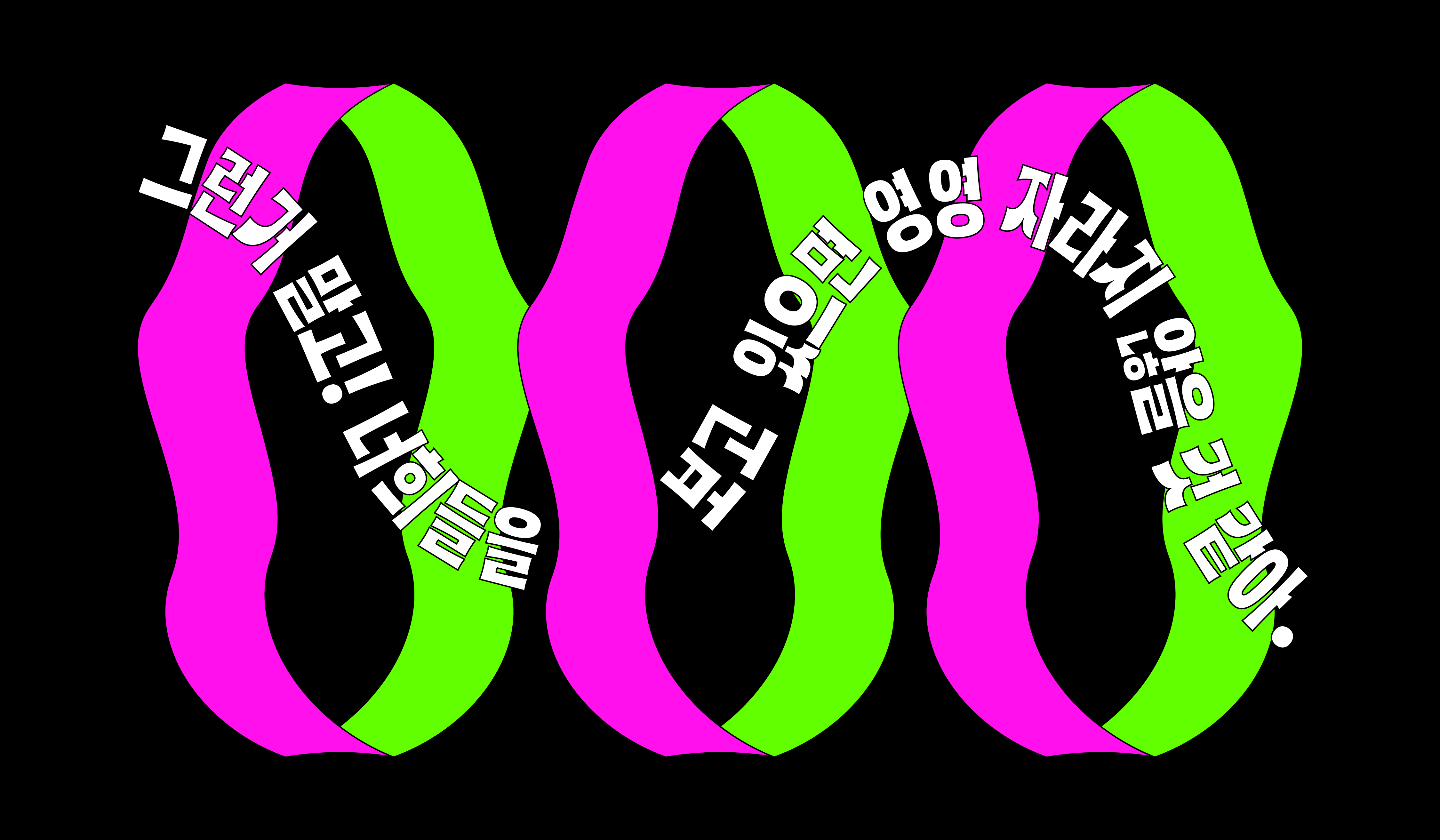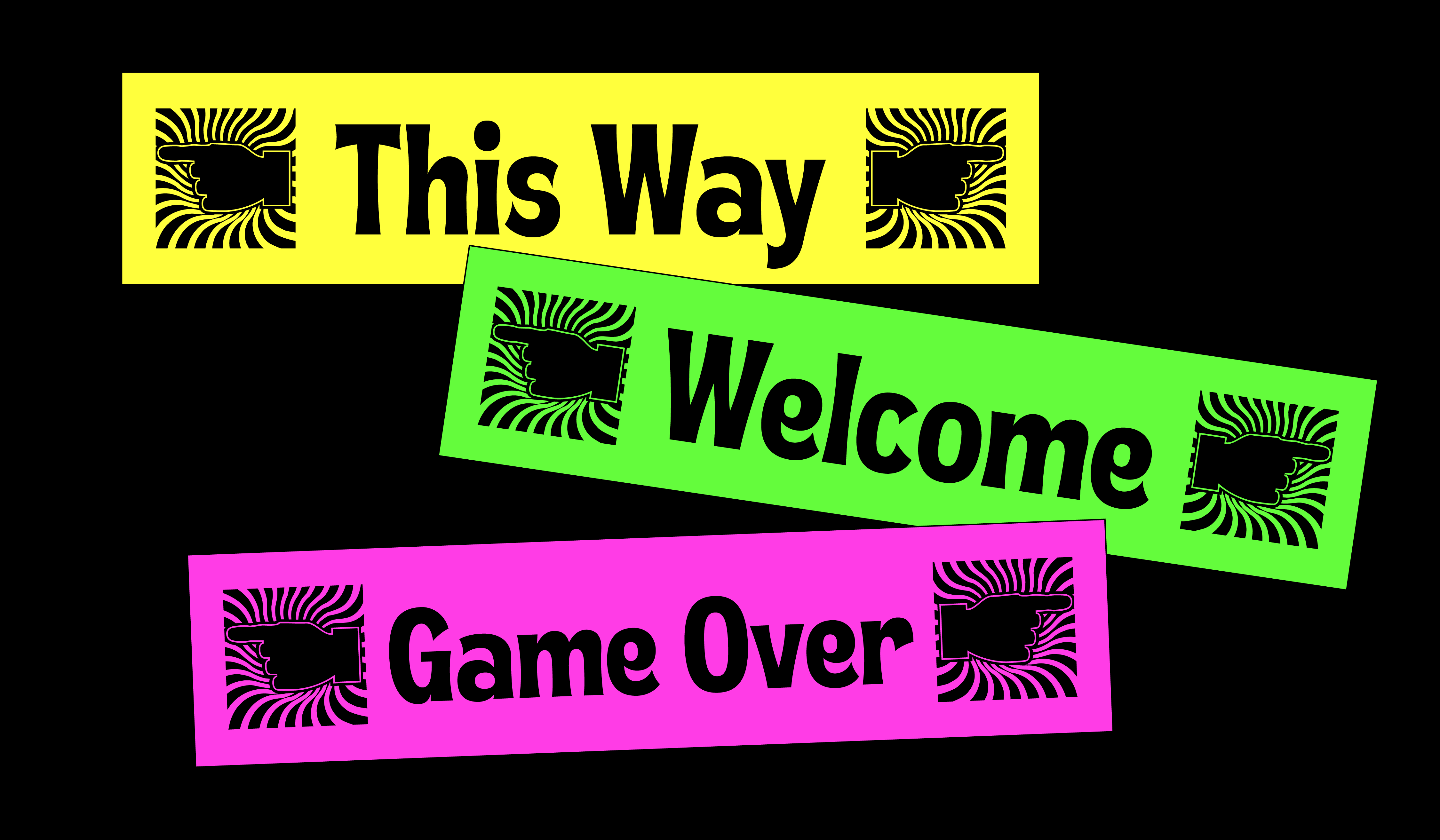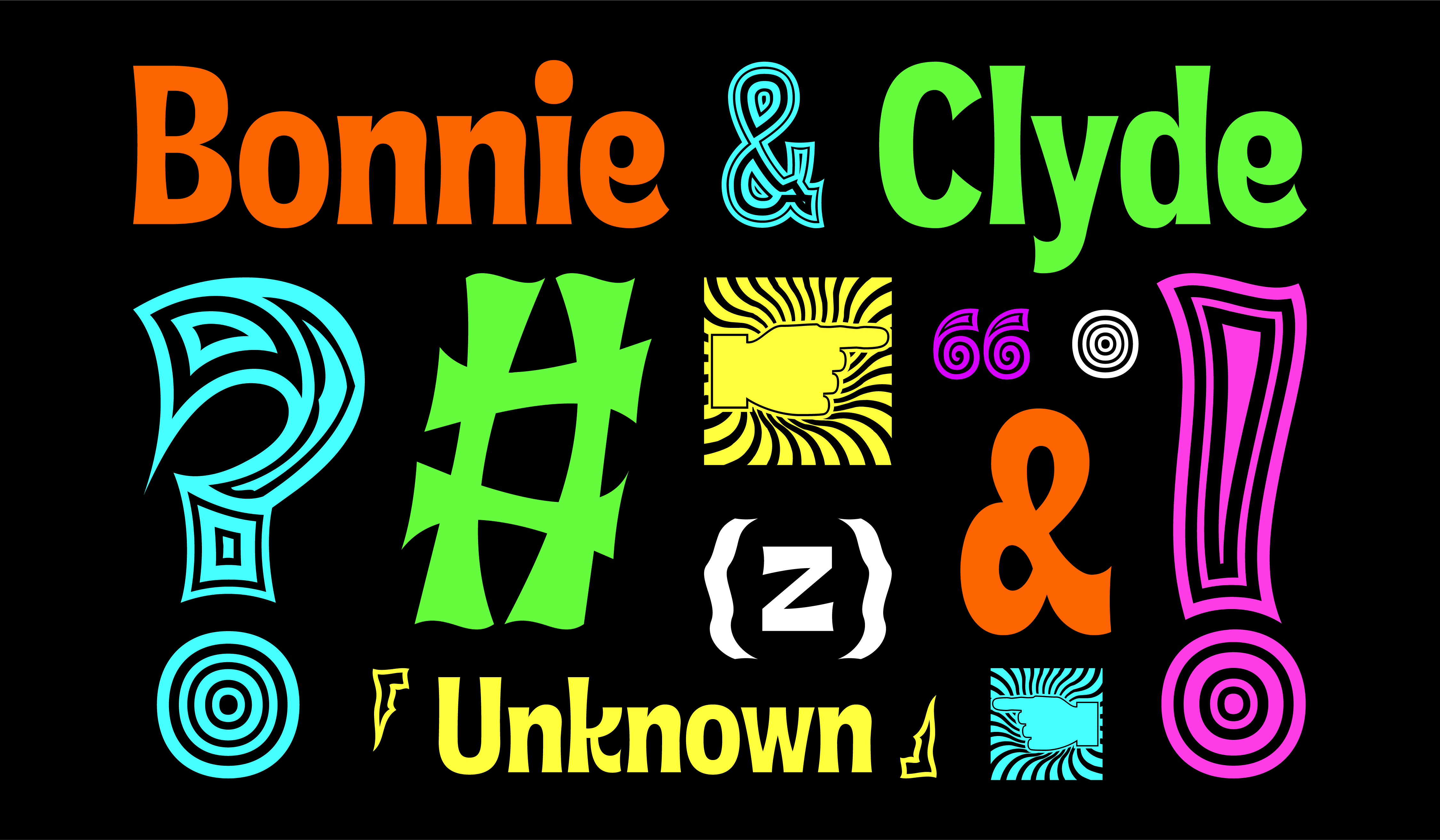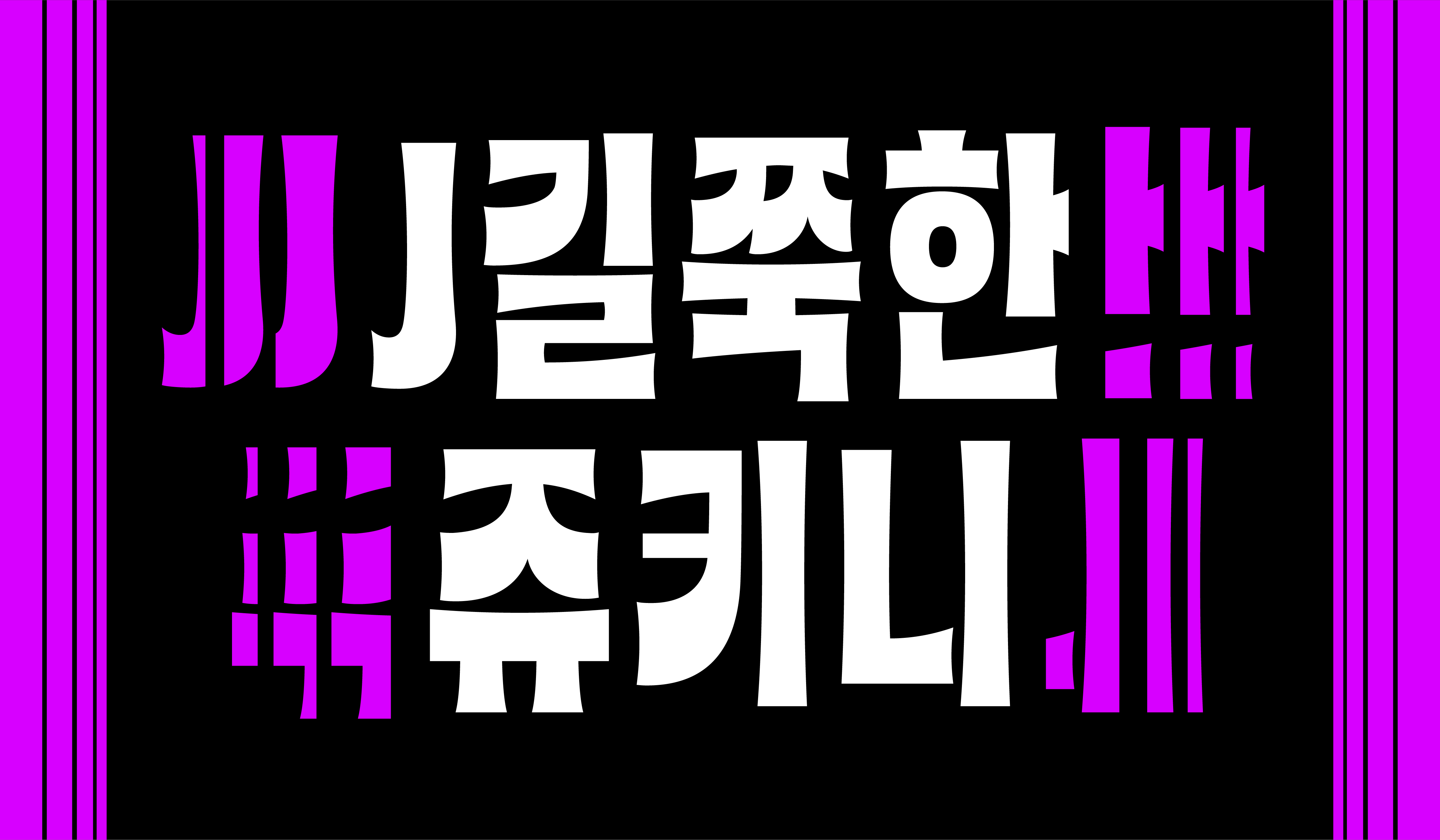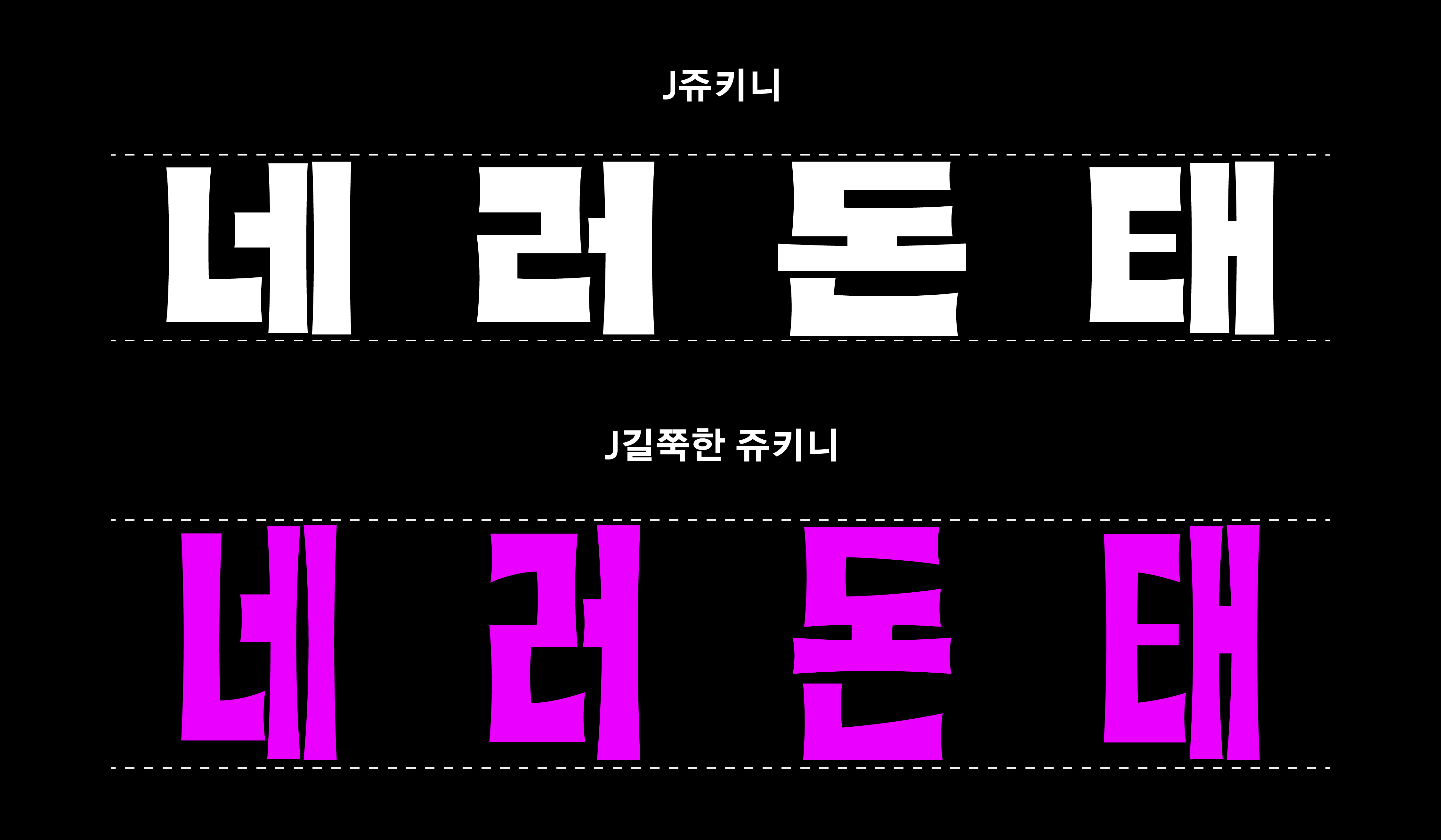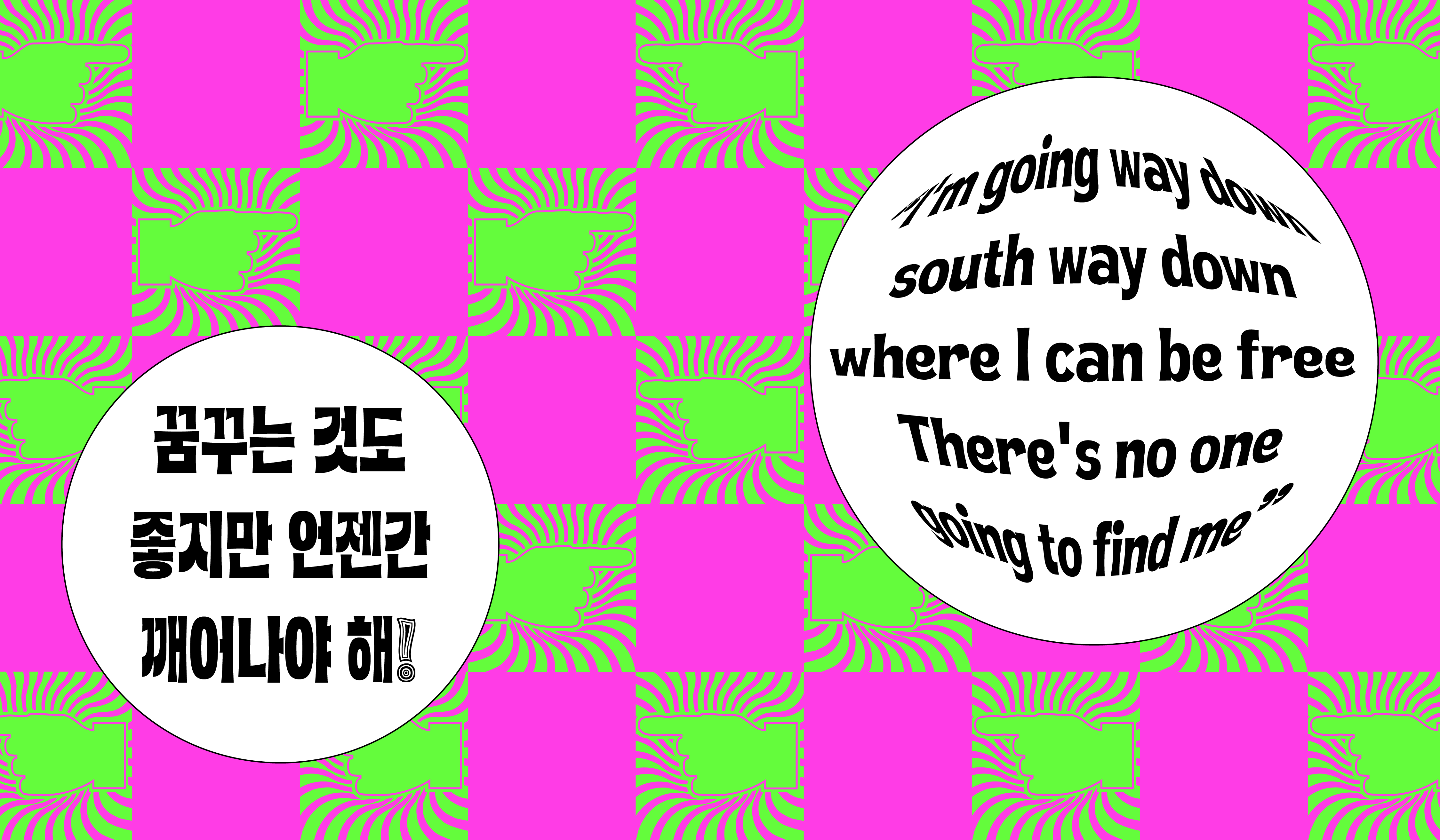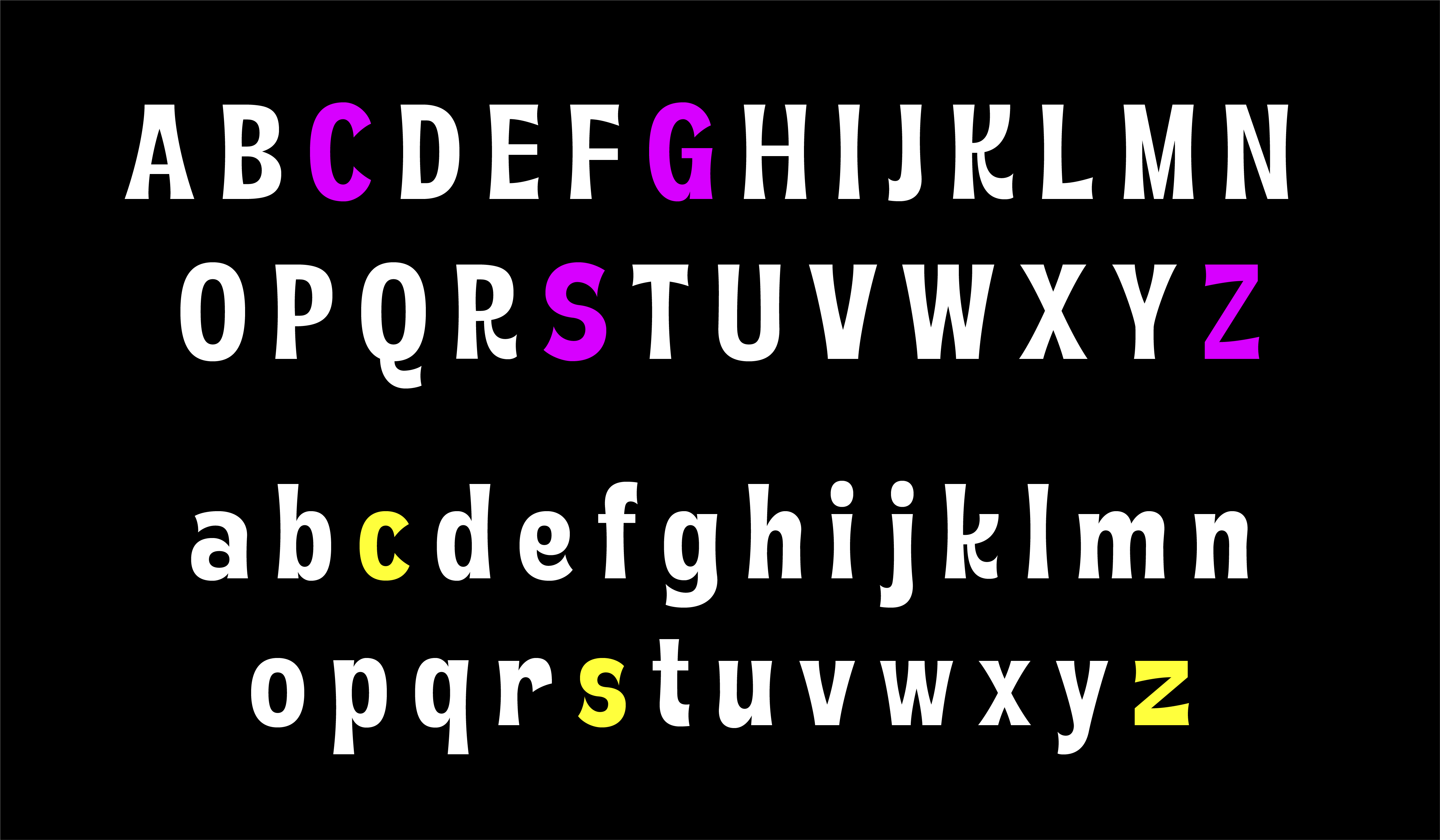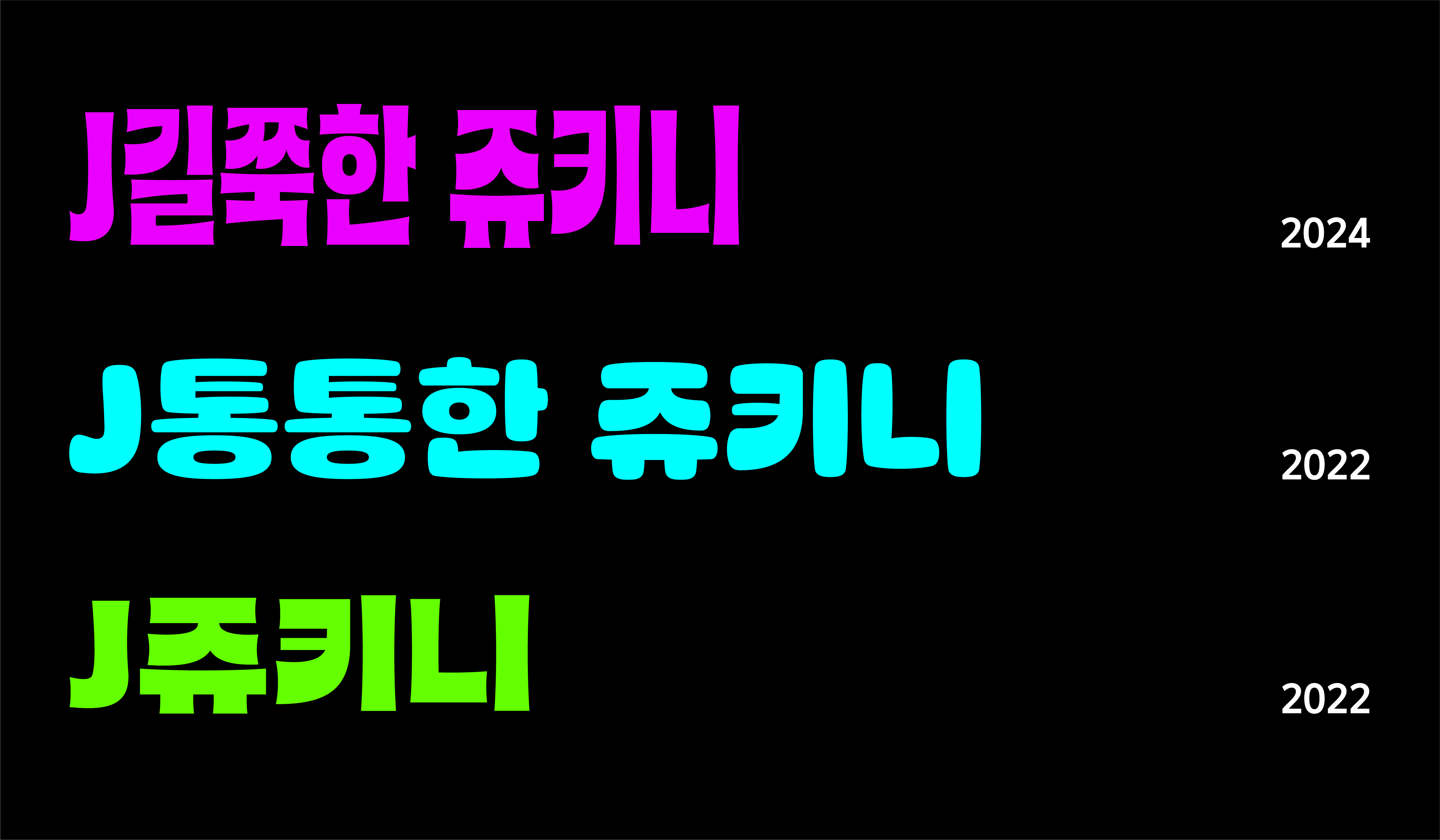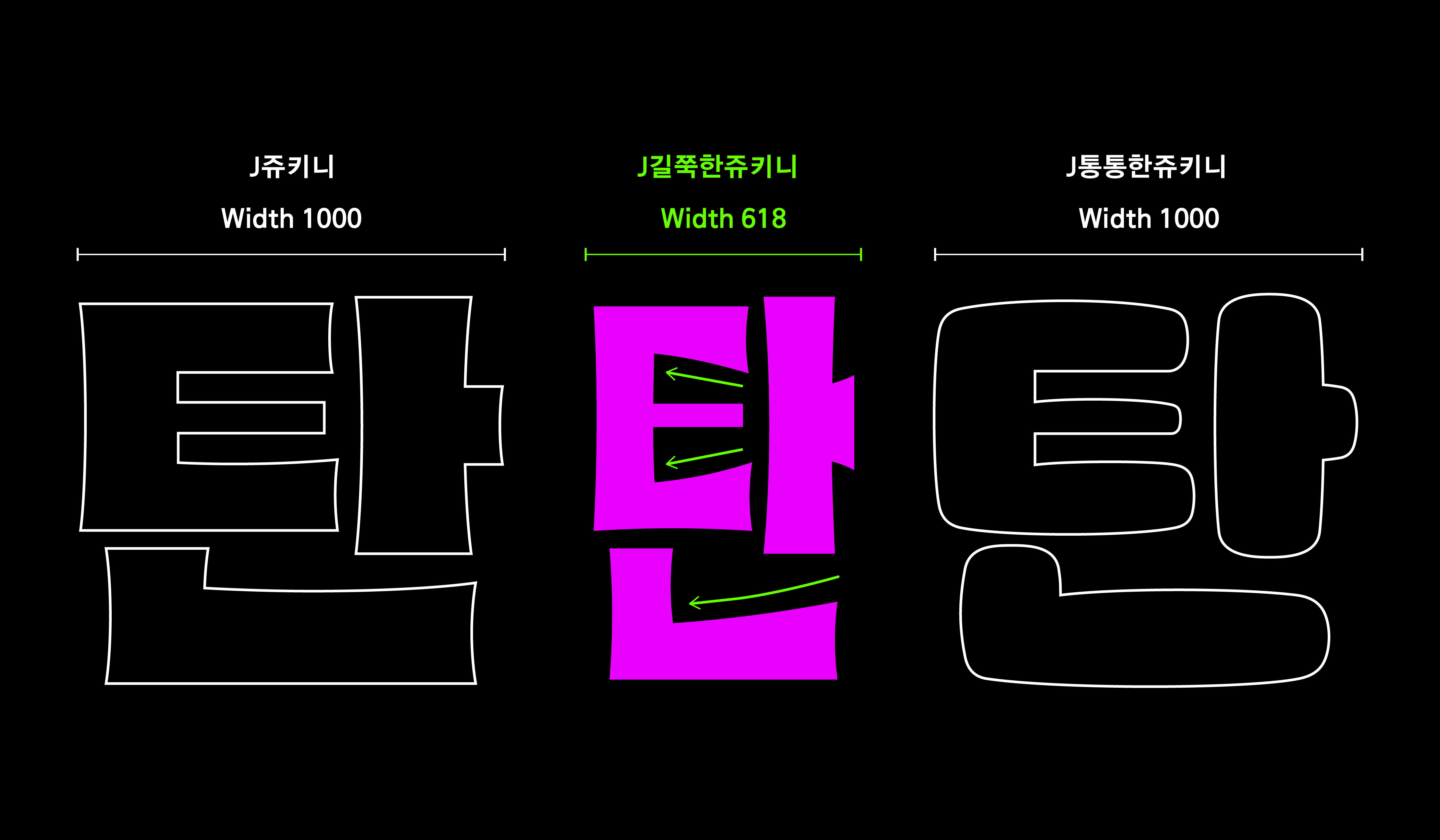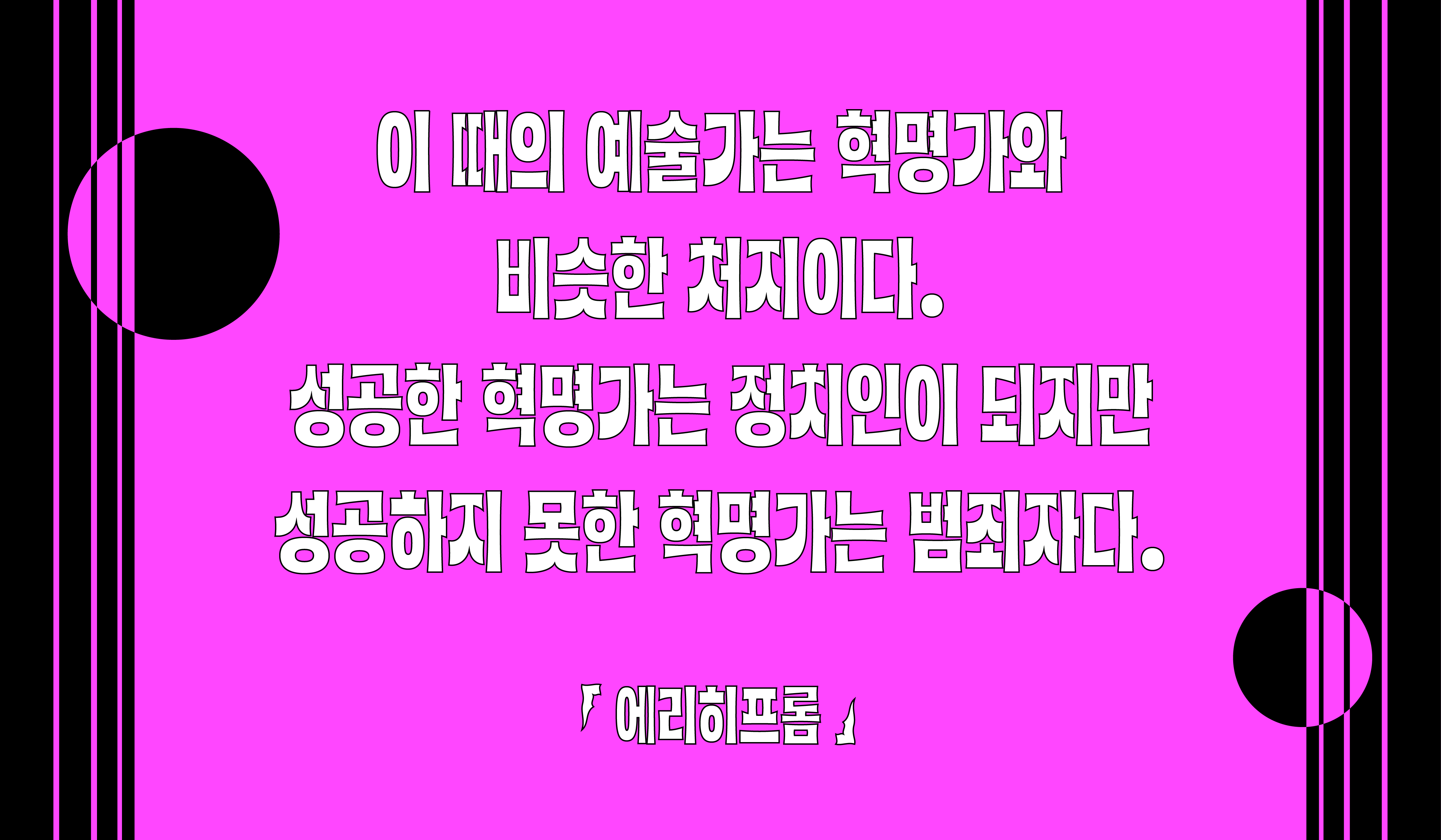
다양한 컨셉으로 활용이 가능하고 독특한 디자인 요소가 많은 서체 시리즈. 개성있는 디테일로 시각적 재미를 더하고 풍부한 이야기를 담을 수 있는 서체이다.
폰트 설명
J길쭉한쥬키니는 J쥬키니(2022), J통통한쥬키니(2022)에 이어 세번째로 출시하는 쥬키니 패밀리입니다.
2022년 첫 출시부터 많은 사랑을 받아온 쥬키니 패밀리 시리즈 중 하나입니다.
이번에는 키가 커진 쥬키니를 확인 할 수 있습니다.
쥬키니 가족구성
쥬키니는 패밀리이지만 각각의 서체마다 개성이 강하고 매력이 있습니다.
쥬키니는 가장 굵은 굵기의 헤비 타이틀용으로만 구성된 패밀리로서 2022년 출시된 쥬키니를 첫 시작으로 꾸준히 가족을 확대하고 있습니다. 획대비와 지읒, 치읓과 시옷의 자소 비대칭, 기억과 키읔의 과감한 사선 획은 패밀리로 유지하되 하나하나의 폰트가 다른 획의 디테일을 가지며 다양한 인상을 표현하는 역동적이며 유니크한 패밀리 구성입니다.
한글디자인
쥬키니의 오목한 획과 자소의 비대칭은 유지하며 길쭉한 쥬키니만의 특징으로 장체와 자소(ㄴ,ㄷ,ㅌ,ㄹ0의 가로획 사선처리고 기획.
두 개의 큰 방향 설정 후 우연히 접하게 된 1960년대 사회문화에 영향을 받은 사이키델릭 포스터는 길쭉한 쥬키니의 디자인 디테일을 잡는데 많은 영향을 주었습니다. 사이키델릭 포스터에 종종 등장하는 메세지를 전달하는 도구로 사용된 글자 형태는 장체에 오목한 획, 그리고 다소 왜곡된 곡선과 획으로 표현된 것을 볼 수 있었고 이를 길쭉한 쥬키니의 디자인 특징으로 잡고 시작했습니다.
Width의 경우 쥬키니는 전각, 길쭉한쥬키니는 618로, 좁아진 가로폭안에서 가로획과 세로획의 변화가 생겼고, 이전 쥬키니 패밀리와는 다른 사이키델릭에서 보여지는 과감한 선과 획에서 주는 디테일을 길쭉한쥬키니의 가로획에 사선 처리를 하여 좁아진 가로폭 안에서 생기는 굵기의 불균형과 같은 시각적 문제를 동시에 해결할 수 있었습니다.
라틴디자인
쥬키니의 패밀리로서 디자인의 유사성과 동시에 길쭉한 쥬키니만의 디테일을 가져갔습니다.
A, K, R, H, M, N, Q, a, b, g, h 는 디자인은 유지하며 장체 형태로 가져가고 C, S, G, Z, c, s, z 은 길쭉한 쥬키니의 특징을 더하였습니다.
특수문자, 기호
한글디자인에서는 쥬키니 패밀리로서 사이키델릭 컨셉에 충실하게 표현된 문장부호 추가 글립이 있습니다.
옵티컬하고 날카로운 선으로 조금의 그로테스크한 요소가 돋보이는 문장부호를 함께 사용 할 수 있습니다.